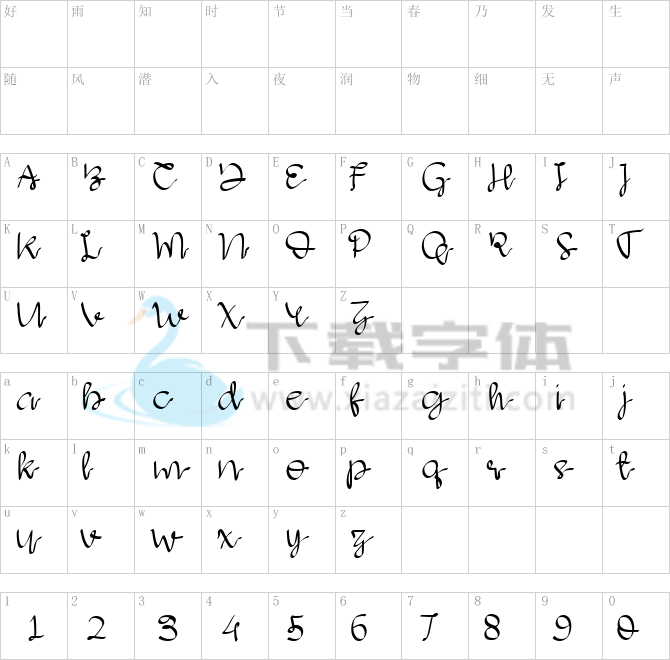
Agathsya.ttf字体下载
Agathsya.ttf字体下载,这款字体结构工整、笔画清晰,兼顾美观与易读性,适用于标题、正文、海报、包装、LOGO 等多种场景。字形优雅稳定,风格百搭耐看,适配日常排版与创意设计,让文字呈现更舒适、更具质感。Agathsya.ttf字体下载一笔一画,皆是细节,以均衡的比例、流畅的线条打造舒适视觉体验,字形端正大气,风格简约现代。无论是商业设计、品牌宣传还是日常排版,都能轻松驾驭,让文字更有格调与力量。Agathsya.ttf字体下载字体下载。